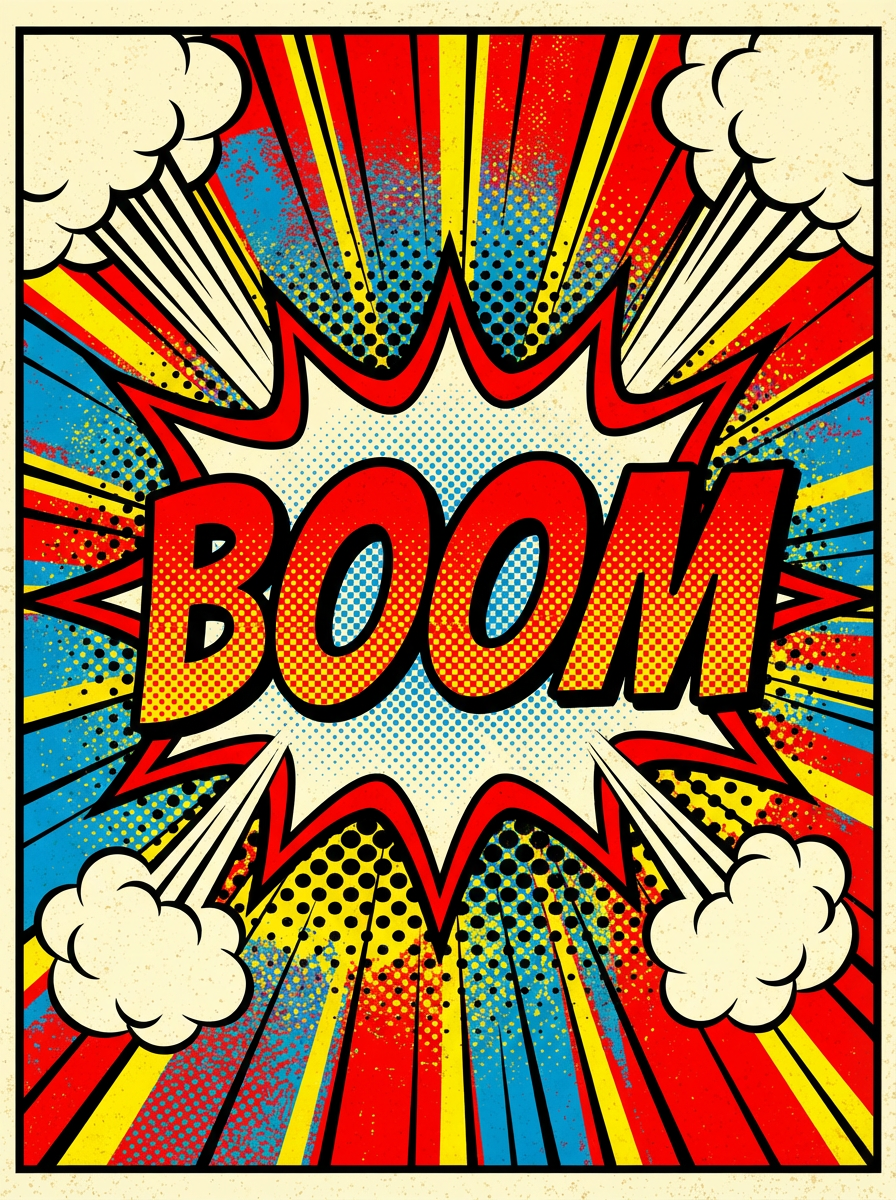
一键生成波普风格字体设计
提示词:波普艺术风格字体爆炸效果,复古漫画风,画面中心为超大号波普字体文字“BOOM”(文字即主视觉),手绘漫画字体,粗黑描边,高对比度亮色配色(红 / 黄 / 蓝),放射状爆炸线条,漫画半色调网点纹理(halftone dots),文字外轮廓为爆炸形 / 对话气泡形,1960 年代美式漫画风格,平面图形设计,强烈视觉冲击力,复古印刷颗粒质感背景